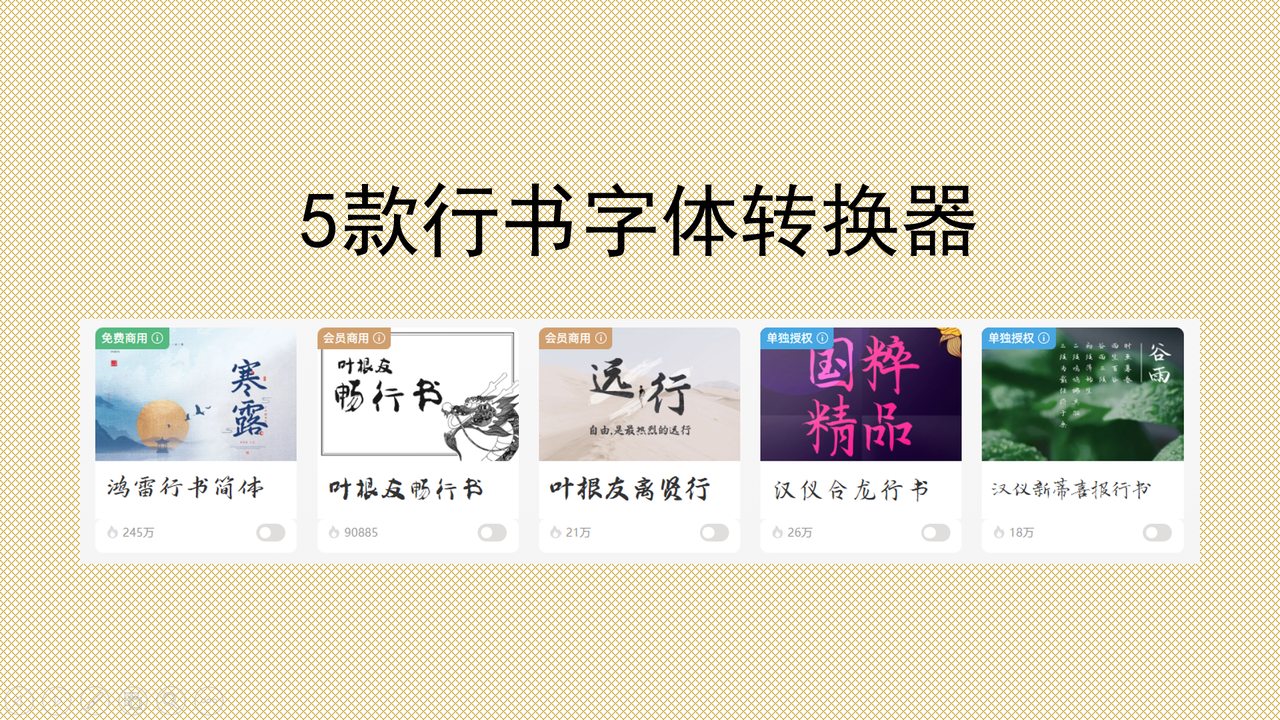
行书字体转换器:5 款免费工具,文字秒变古风书法
想要让诗词排版更有传统气息?想要让古风海报标题更有笔墨气质?行书字体转换器就是你的高效助手!其实我们很多人都不是专业学习书法的,手动临摹行书耗时且耗力,一些专业设计软件的门槛又很高,没个三五年经验很难自己设计出行书字体。优质的行书字体转换器可以帮助你快速将普通的文字转换为行书风格,没有书法基础也可以拥有标准的行书字体!接下来推荐的这 5 款免费行书字体转换器可要好好收藏,带你一秒走进古风世界,体验行书字体给作品增加的魅力!
一、字由
用户只需要在字体资源内搜索行书字体,选择自己满意的字体,输入文本内容,就能一键将字体转换为行书风格。而且它还可以直接批量预览试字,我觉得这一点非常方便,用户直接在预览框输入需要的文本内容,就可以查看每款行书字体的呈现效果,非常便于大家选择。
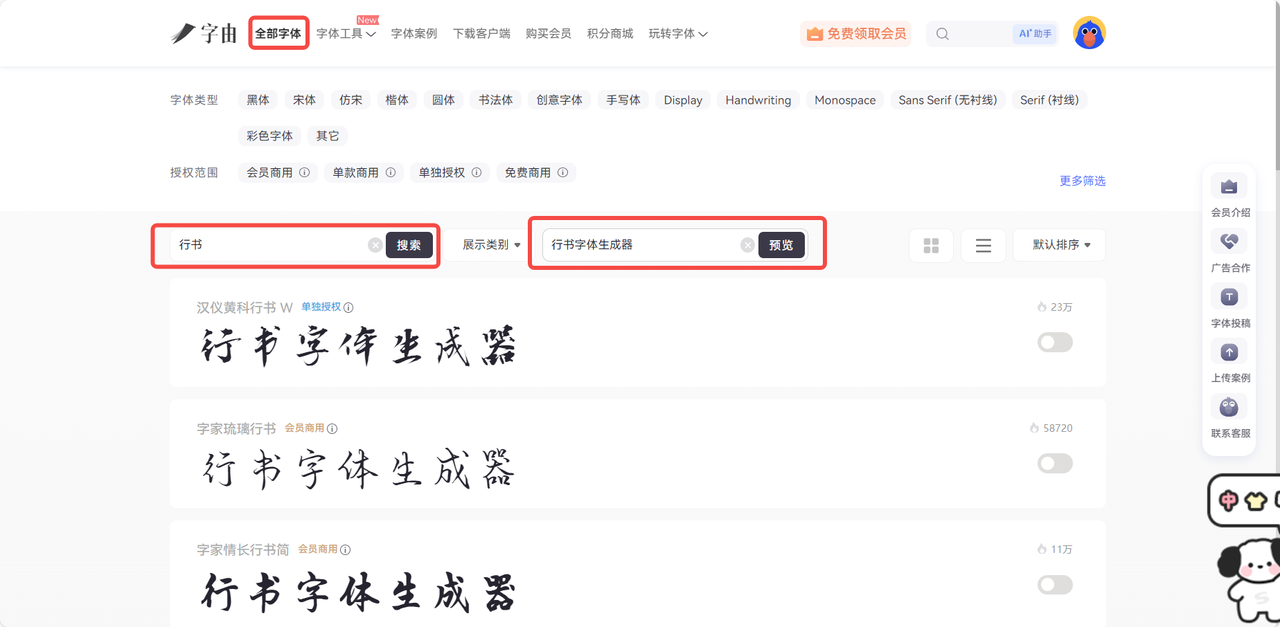
二、FontSpace
FontSpace 是国际设计师信赖的行书字体库,包含超 10000 种免费字体,涵盖毛笔行书、复古手写、现代行书等风格,是找行书字体的“宝藏库 ”。用户只需要输入文字内容,筛选行书标签,就可以实时预览不同字体的效果,非常直观清晰。在 FontSpace 上,每款字体都清晰标注了个人或商业授权,且支持下载 PNG 透明背景图。唯一的缺陷是,部分字体仅支持英文,中文的呈现效果很一般。
三、Cool Text
Cool Text 是一款老牌的行书字体转换器工具,在“Handwritten”分类下提供 30+ 预设行书特效,比如毛笔烫金、复古、水墨、晕染等,且这些特效完全免费使用,新手 30 秒即可生成炫酷行书标题。 最值得一提的就是,Cool Text 可以一键生成行书特效,用户只需要选择特效模板,输入文字,然后调整颜色、字间距、阴影等文字基础效果,就可以在线获得一个新的行书字体。我觉得这个工具上的字体风格更适合用于用游戏界面或是科技未来电影的标题,酷炫感和科技感拉满。Cool Text 转换的行书字体支持 PNG/JPEG 下载,部分特效支持矢量SVG导出。
四、Calligraphr
Calligraphr 是加拿大开发的一款创新型字体转换生成平台,与其他的行书转换器不同,它以 AI 技术为核心,支持用户自主创建专属的行书字体。它最大的优势在于字符随机化,也就是说它可以模拟真实手写的过程,意味着你可以为每个字符指定不同的变体,这些变体会在书写过程中随机使用,使字体看起来更自然。该工具拥有图像编辑器,可以对转换后的行书笔画进行微调,比如调整笔画粗细过渡、字间距、字符高度等等,有效提升字体的呈现效果。
同样,Calligraphr 还可以支持个性化复刻行书字体,用户可以下载一个行书模板,用毛笔或钢笔书写文字后上传图片,它能自动识别笔画轨迹以及结构形态,转换为 TTF/OTF 标准字体文件,完美保留个人手写行书的笔触、连笔习惯与风格特征,实现 “手写即字体” 的定制化体验。最关键的是,它还支持连笔字自定义设置,转换时自动匹配替换,贴合行书的书写逻辑。
五、Refont AI
Refont AI 主要t聚焦艺术字的字体转换,是海外功能最全面的行书艺术转换工具,最大的特点就是“适配多风格+智能优化”。该工具在设计之余,内置的AI模型深度学习了王羲之、米芾等中国行书大家的书法风格,基本上可以还原行书的下笔。Refont AI 可以一键转换成行楷、行草、现代创意行书等多种风格,覆盖了古典、简约、个性等多个效果风格,满足了设计师的日常需求。
用户只需要输入想要生成的文字,Refont AI 会自动生成多种行书效果,你可以自由切换风格、调整笔画粗细、墨色深浅,而且还能添加晕染、飞白等毛笔效果,简直就像是手写出来的行书字体,增强了很多艺术表现力。为了便于用户的使用体验,该工具提供多元化的导出方案,可以选择导出为SVG矢量图、JPEG高清图片、透明底图等,可以直接用于后续的海报设计、网页设计、包装设计。除此之外,它支持段落内容批量转换,这是目前很多行书转换器做不到的一点。
行书字体具有楷书的规整以及草书的灵动,是古风设计的核心元素,经常被用于国风海报、文创产品、婚礼请柬等场景。选择行书自己转换器的时候可以优先选择支持免费商用的工具,这里首选推荐字由。上述给大家介绍过的 5 款免费工具已经可以满足日常的设计需求了,收藏起来,下次需要行书字体的时候就能轻松搞定,让你的设计更具文人笔墨气息!